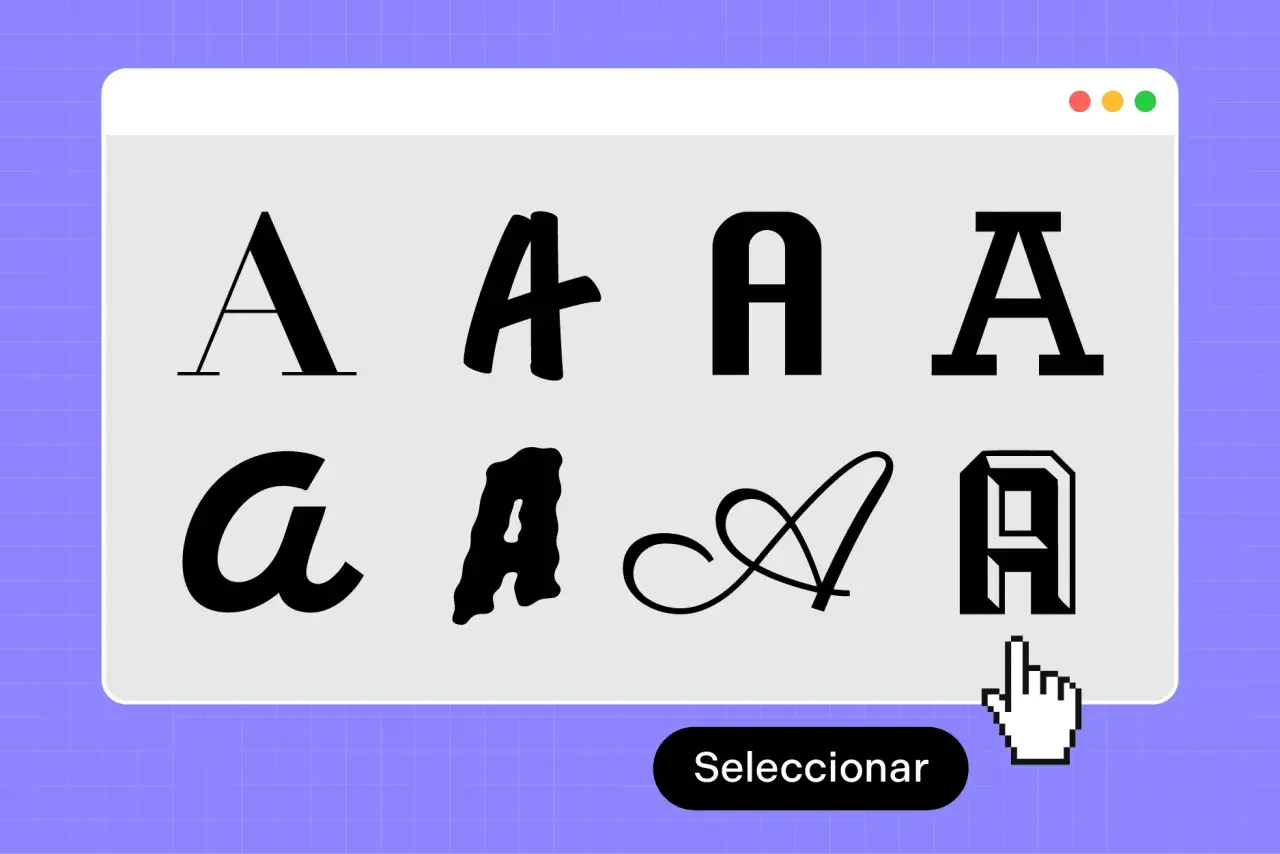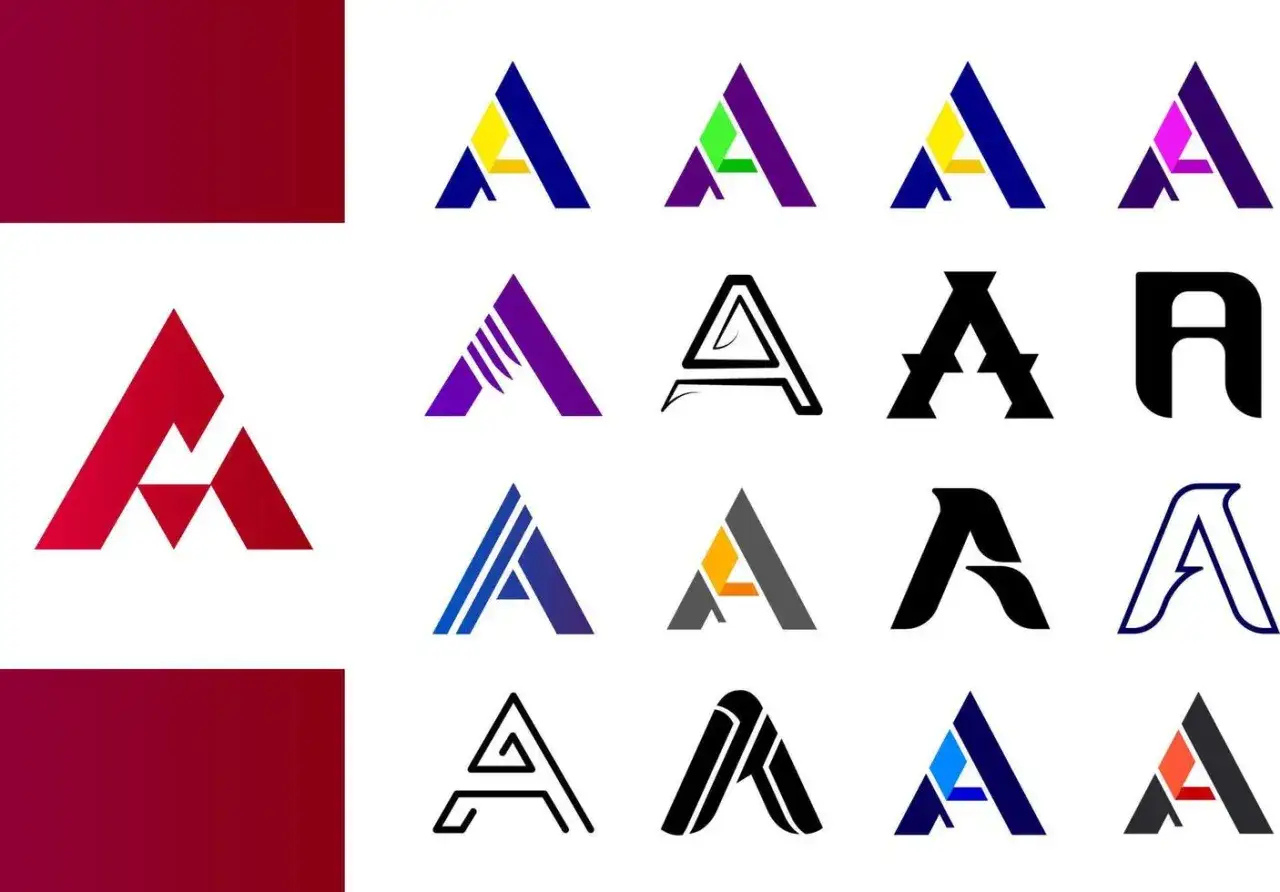
Tipos de A mayúscula en tipografía y cómo elegir la adecuada
Explora diversos tipos de A mayúscula, desde clásicas hasta modernas, en esta ventana de selección.
La A mayúscula cambia mucho más de lo que parece: no transmite lo mismo una A romana con serifas que una A sans serif limpia, una A caligráfica o una A gótica. En este artículo repaso los tipos de A mayúscula que más se encuentran en tipografía, qué rasgos los distinguen y cómo elegir la variante adecuada para logos, títulos, invitaciones, rotulación o proyectos creativos. Si trabajas con diseño, lettering o manualidades, entender estas diferencias te ahorra decisiones torpes y mejora el resultado final.
La A capital se entiende mejor por su función que por su forma
• La forma de la A depende de la familia tipográfica, el grosor y el contexto de uso.
• Las variantes más comunes son romana con serifas, palo seco, caligráfica, gótica y display.
• La anatomía de la letra importa: travesaño, contraforma, remates y contraste cambian la lectura.
• Para piezas pequeñas conviene priorizar legibilidad; para títulos, personalidad; para branding, coherencia.
• Los errores más frecuentes son el exceso de ornamento, el poco espacio y mezclar estilos sin criterio.
Por qué una misma letra puede cambiar tanto
La A no es una forma cerrada y universal; es una familia de soluciones visuales. Cuando cambian las serifas, la inclinación, el contraste o la proporción, cambia también el tono emocional del texto. Una A robusta y geométrica suele sentirse contemporánea; una A con remates finos y eje marcado, más editorial; una A escrita a mano, más cercana y artesanal.
Yo no miro la A como una letra aislada, sino como una pista del resto de la tipografía: si la inicial promete elegancia, el conjunto debería sostener esa promesa. Cuando eso no ocurre, el resultado se ve impostado aunque la letra, por separado, sea bonita. Con esa base, conviene ver qué formas concretas aparecen más a menudo.
Variedad de diseños de la letra A mayúscula, cada uno con un estilo y color único.
Los estilos más habituales de la A capital
En la práctica, las variantes más reconocibles de la A capital se ordenan por estilo y por intención, no por un único estándar técnico. Esta tabla resume las formas que más conviene distinguir cuando eliges una fuente o diseñas una letra a mano.
Estilo Cómo se reconoce Qué comunica Uso donde mejor rinde
Romana con serifas Trazos equilibrados y pequeños remates Tradición, orden y confianza Editorial, libros, packaging cuidado
Palo seco Sin remates y con dibujo limpio Modernidad, claridad y neutralidad Logotipos, interfaces, señalética
Caligráfica o script Trazo fluido, a veces unido y con ritmo manual Cercanía, elegancia y movimiento Invitaciones, firmas, papelería creativa
Gótica Ángulos marcados y presencia muy ornamental Historia, dramatismo y fuerza visual Títulos puntuales, carteles temáticos
Display o decorativa Diseño singular, a veces experimental Personalidad y foco Portadas, branding, piezas promocionales
Uncial o manuscrita Formas redondeadas y aspecto artesanal Calidez, antigüedad y carácter manual Proyectos artesanales, álbumes, decoración
Una matización útil: la versalita no es otro dibujo de la A, sino una capital reducida en altura y pensada para una jerarquía más discreta. Sirve bien en detalles editoriales, pero no sustituye a una mayúscula normal cuando hace falta presencia. Para afinar la elección de verdad, hace falta mirar la anatomía de la letra y no solo la etiqueta del estilo.
Qué cambia de verdad en la anatomía de la A
Yo suelo fijarme en cinco cosas antes de decidir si una A funciona: la forma del travesaño, el espacio interno, el grosor de los trazos, la presencia de remates y la proporción general. Son los rasgos que determinan si la letra respira, si aguanta una reducción o si se convierte en un adorno difícil de leer.
Serifas y remates
Las serifas son los pequeños remates al final de los trazos. En una A romana aportan tradición y ayudan a que la letra se asiente; en una pantalla o en un vinilo muy pequeño, sin embargo, pueden perderse o ensuciar la forma. Por eso no las trato como un detalle menor: cambian el carácter entero de la pieza.
Travesaño y contraforma
El travesaño es la barra interior de la A; la contraforma es el hueco que queda alrededor. Cuando el travesaño está demasiado bajo, la letra se vuelve pesada; si está demasiado alto, la A puede parecer débil. Yo suelo mirar ese equilibrio porque define la respiración visual de toda la palabra.
Contraste y modulación
El contraste es la diferencia entre trazos finos y gruesos, y la modulación describe cómo cambia ese grosor a lo largo de la curva. Una A con contraste alto comunica elegancia, pero también exige más cuidado en tamaños pequeños. En cambio, un trazo monolineal, cuando el grosor se mantiene casi constante, suele funcionar mejor en piezas muy limpias o técnicas.